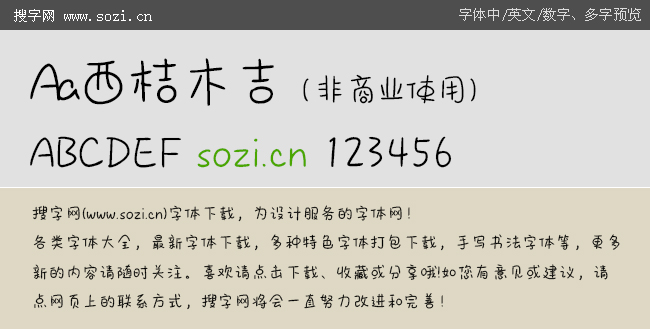
Aa西桔木吉
搜字網(wǎng)給大家提供一款A(yù)a西桔木吉(非商業(yè)使用)中文字體下載,Aa西桔木吉是一款卡通風(fēng)格的手寫字體,這款字體字形圓潤可愛,富有趣味性,具有很好的視覺感。適合應(yīng)用于藝術(shù)設(shè)計(jì)、平面宣傳設(shè)計(jì)、網(wǎng)頁設(shè)計(jì)、海報(bào)設(shè)計(jì)等應(yīng)用(此字體為個(gè)人非商用版,商用可以聯(lián)系QQ:1006760504)。